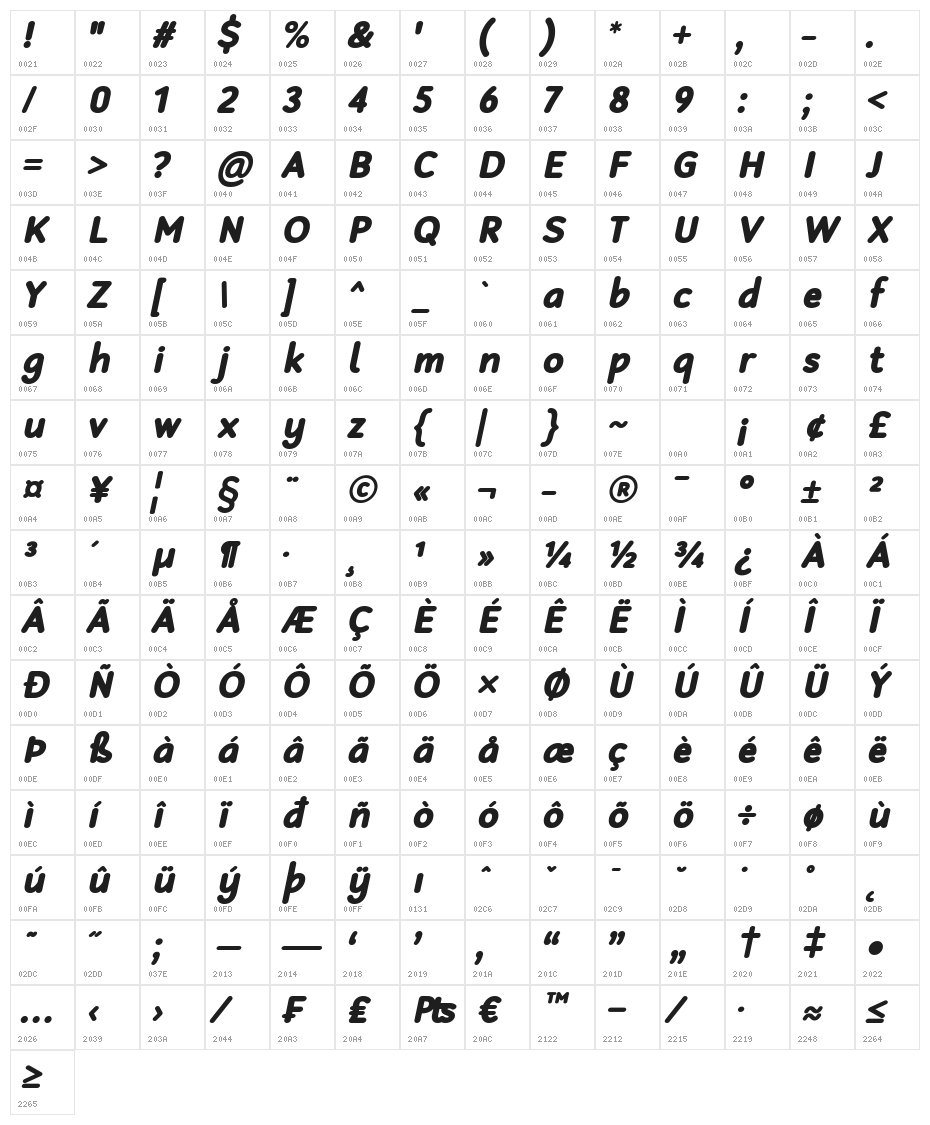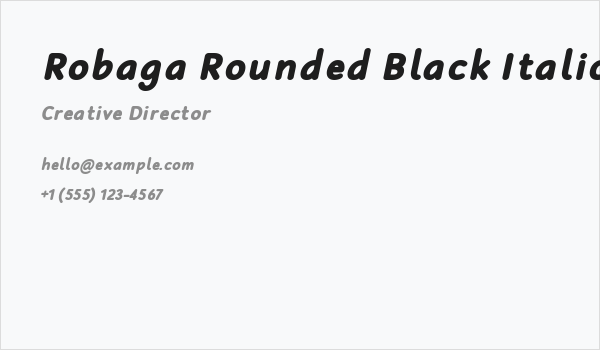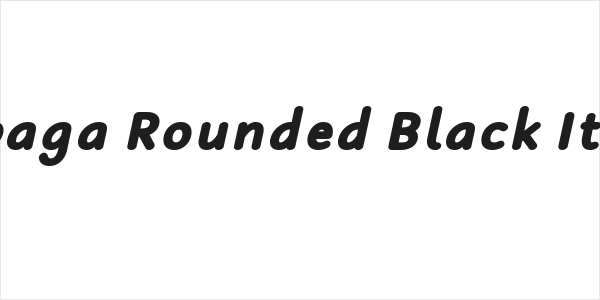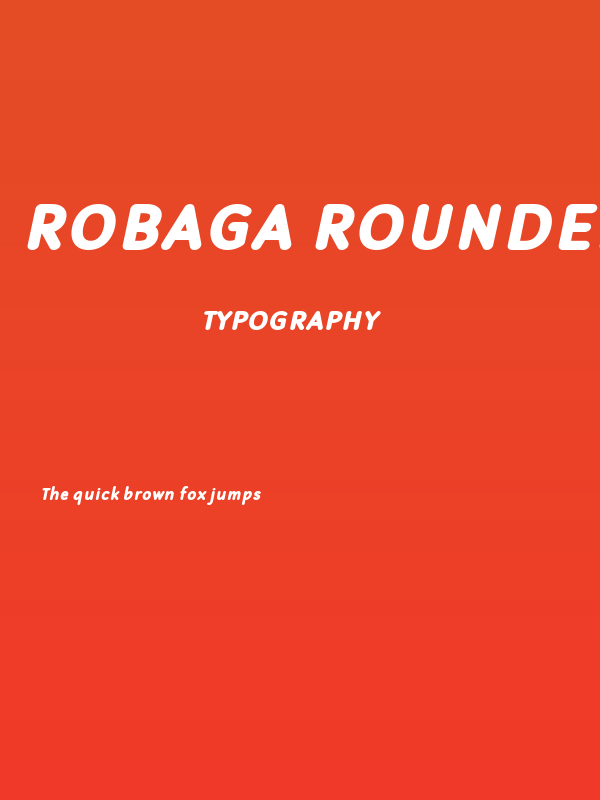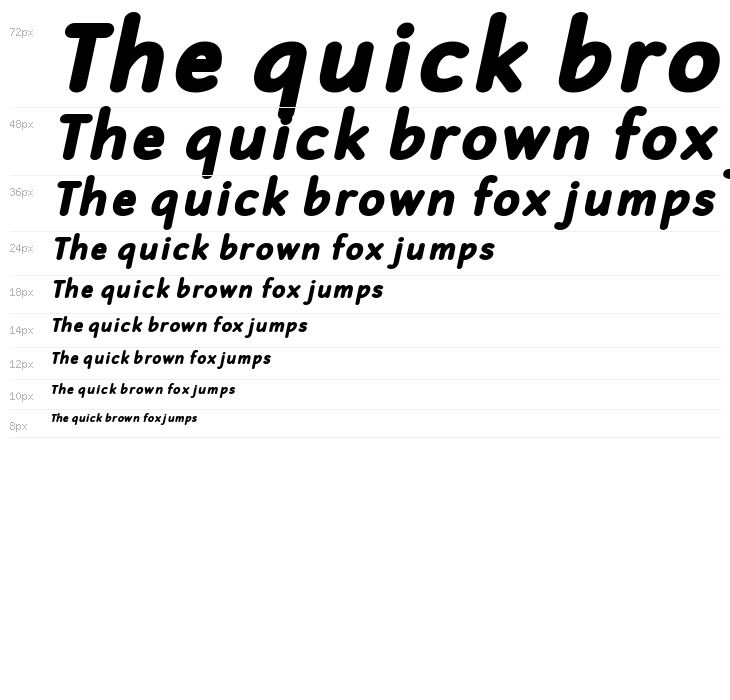
Robaga Rounded Black Italic Font
| Progetti proposti | Ideal for branding, headlines, posters, and advertising materials where a strong and friendly presence is desired. |